Khi thiết kế logo thương hiệu cá nhân, thiệp cưới cao cấp hay banner quảng cáo cần tạo điểm nhấn, font chữ ký luôn là lựa chọn rất đáng cân nhắc. Kiểu chữ này mang lại cảm giác mềm mại, cá tính và chuyên nghiệp hơn so với các font thông thường. Tuy nhiên, nỗi ám ảnh lớn nhất của các designer Việt chính là việc tìm được một font chữ ký ưng ý nhưng lại… lỗi dấu tiếng Việt. Việc phải tự ngồi “vẽ” lại từng dấu ngã, dấu hỏi hay chữ “đ” không chỉ tốn thời gian mà còn làm mất đi sự mượt mà tự nhiên của con chữ.
Vì vậy, bài viết này sẽ giúp bạn tiết kiệm công sức khi tìm font. Dưới đây là danh sách hơn 10 font chữ ký Việt hóa đẹp, được chọn lọc kỹ để hỗ trợ tiếng Việt có dấu ổn định, dễ dùng trong nhiều loại thiết kế.
Vì sao font chữ ký được nhiều người yêu thích?
Trong thiết kế chữ, font chữ ký luôn có sức hút riêng. Đây là kiểu font khó bị thay thế bởi các nhóm chữ truyền thống, vì nó vừa mang tính nghệ thuật, vừa tạo cảm giác gần gũi và khác biệt.
- Tạo dấu ấn cá nhân rõ rệt: Dù được tạo ra dưới dạng kỹ thuật số, font chữ ký vẫn gợi cảm giác như được viết tay thật. Những đường nét phóng khoáng, mềm mại giúp thiết kế trở nên tự nhiên, có cá tính và mang dấu ấn riêng hơn.
- Mang lại cảm giác sang trọng: Font chữ ký thường xuất hiện trong các lĩnh vực như thời trang, mỹ phẩm, spa, nhiếp ảnh, thiệp cưới hoặc thương hiệu cá nhân. Kiểu chữ này giúp tổng thể thiết kế trông tinh tế, cao cấp và chuyên nghiệp hơn.
- Giúp thiết kế bớt đơn điệu: Khi đặt một dòng chữ ký mềm mại cạnh các khối chữ vuông vức, bố cục sẽ có điểm nhấn rõ hơn. Đây là cách đơn giản nhưng hiệu quả để thu hút ánh nhìn, tạo cảm xúc và tăng tính thẩm mỹ cho sản phẩm thiết kế.
Top 10+ font chữ ký Việt hóa đẹp, nổi bật theo từng phong cách
Mỗi thiết kế đều mang một tinh thần và thông điệp riêng. Vì vậy, lựa chọn đúng font chữ không chỉ giúp bố cục đẹp hơn mà còn quyết định cảm xúc người xem nhận được. Dưới đây là 10 font chữ ký đẹp mà chúng tôi muốn chia sẻ đến các bạn:
Romantically
Romantically mang đúng tinh thần lãng mạn như tên gọi. Font có nét chữ mảnh, mềm và uốn lượn nhẹ nhàng. Kiểu chữ này rất hợp để viết tên cô dâu chú rể trên thiệp cưới, thiết kế logo tiệm hoa, tiệm bánh hoặc các ấn phẩm mang phong cách nữ tính.
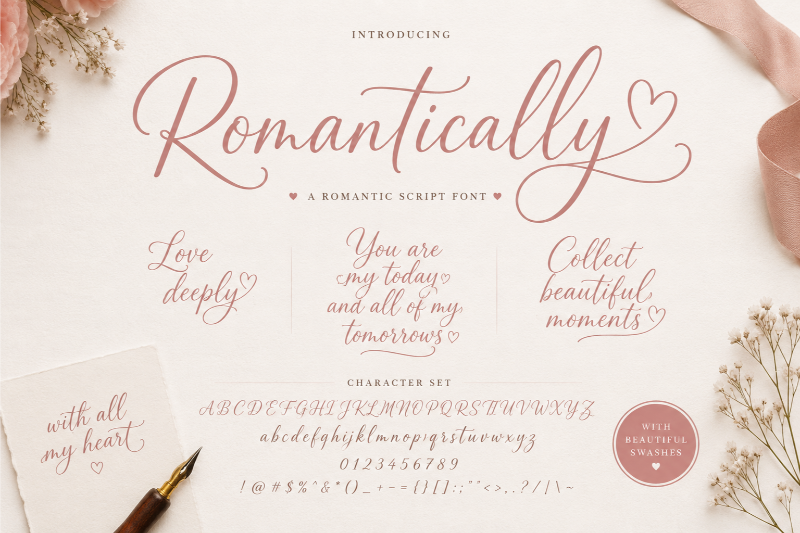
Rossela
Rossela tạo cảm giác hiện đại, thanh thoát và có độ quyến rũ vừa phải. Font không quá cầu kỳ nhưng vẫn đủ nổi bật, phù hợp với thương hiệu mỹ phẩm, thời trang nữ, spa hoặc các thiết kế cần sự sang trọng nhẹ nhàng.
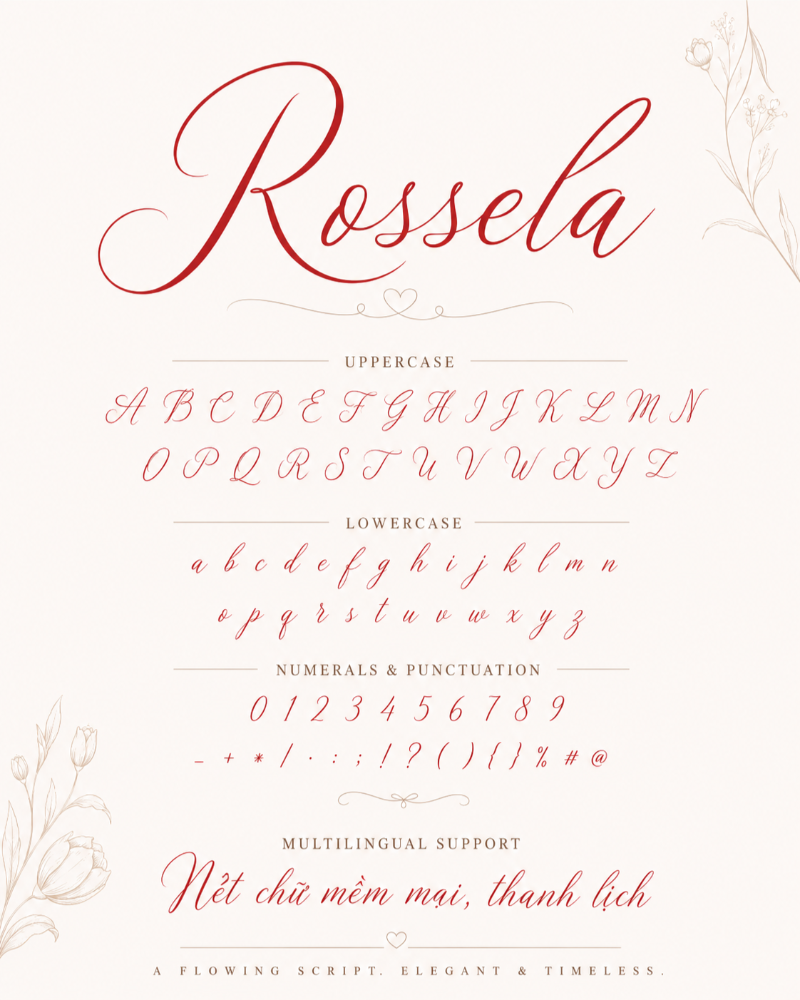
Imogen Agnes
Imogen Agnes gây ấn tượng nhờ nét chữ tự nhiên, giống chữ viết tay bằng bút mực. Các đường nét có cảm giác phóng khoáng, hơi vội nhưng vẫn sắc sảo. Font này phù hợp để làm chữ ký cuối bài blog, quote cảm xúc, watermark ảnh hoặc các thiết kế mang hơi hướng cá nhân.
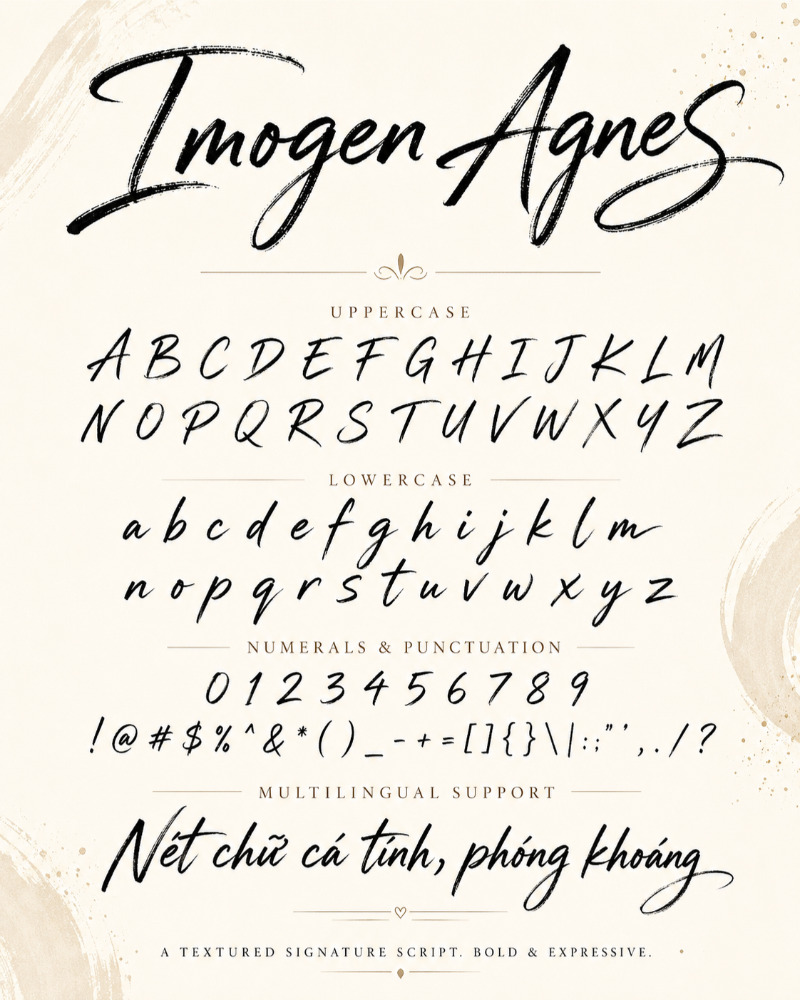
Hipsteria
Hipsteria mang màu sắc vintage rõ rệt, pha chút bụi bặm của văn hóa hipster. Nét chữ có phần thô, không quá trau chuốt nhưng lại tạo cảm giác rất nghệ thuật. Đây là lựa chọn phù hợp cho watermark nhiếp ảnh, logo quán cà phê, barber shop hoặc các thương hiệu theo phong cách đường phố.
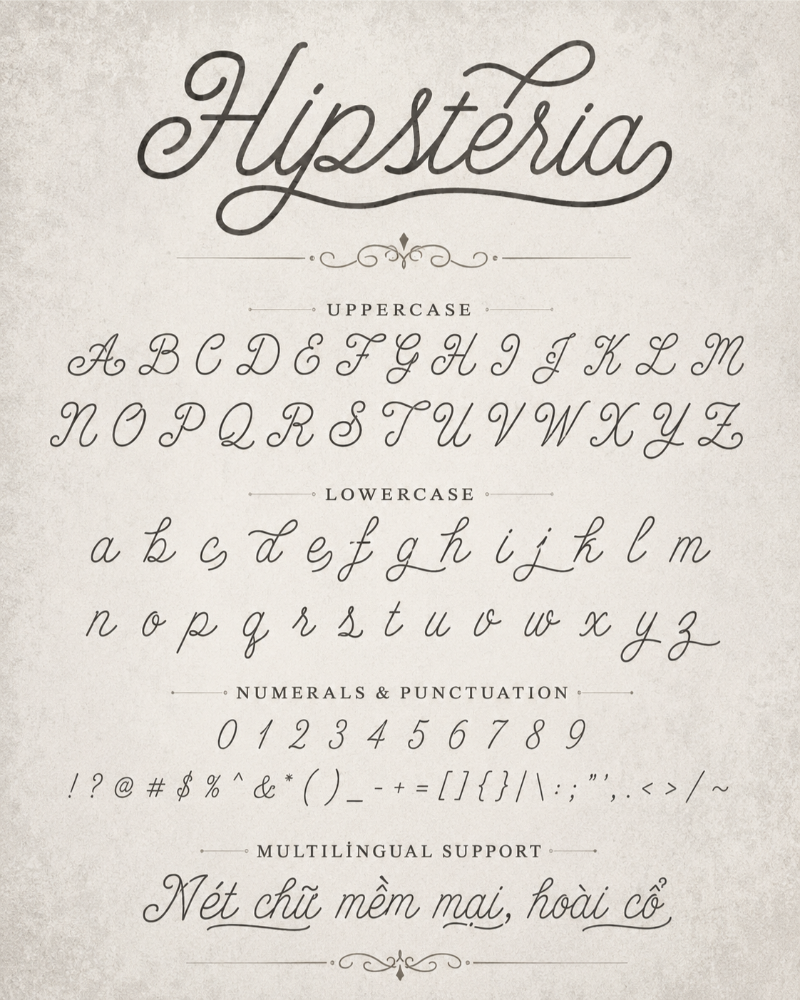
Just Awesome
Just Awesome nổi bật với nét chữ dày, mạnh và dứt khoát. Font này tạo cảm giác năng lượng, tự tin và rất dễ thu hút ánh nhìn. Bạn có thể dùng Just Awesome cho poster sự kiện, bìa album, banner quảng cáo hoặc các thiết kế cần sự cá tính rõ ràng.
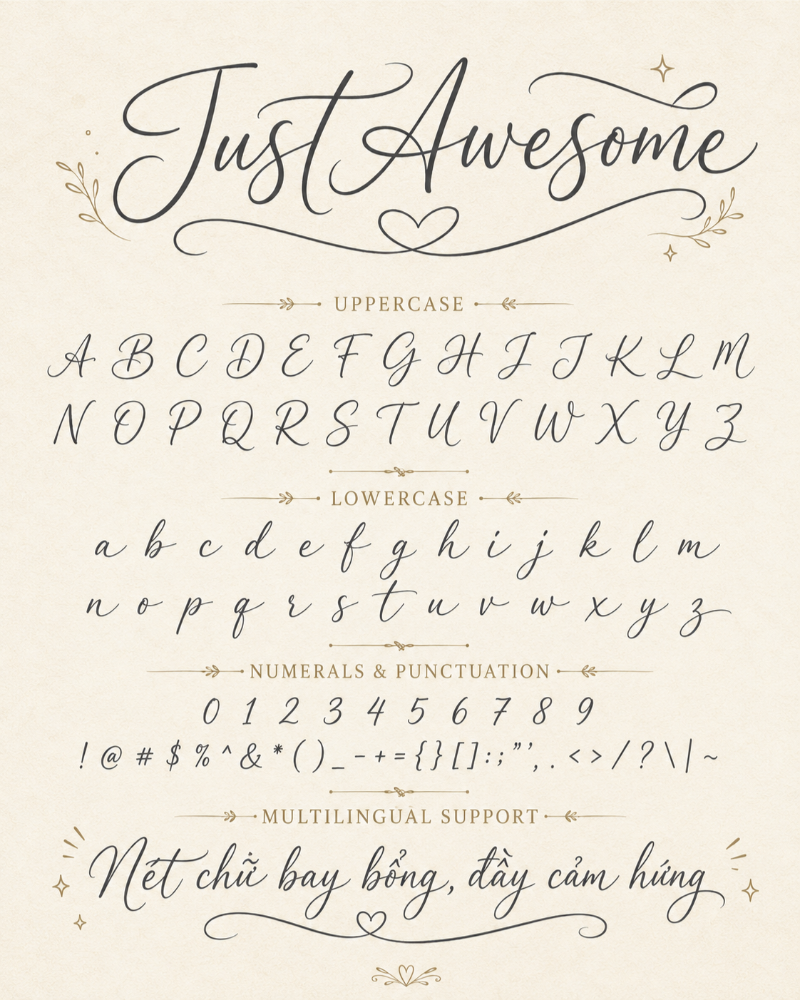
Bellwethers
Bellwethers có độ tương phản rõ giữa nét thanh và nét đậm, tạo cảm giác sang trọng và nghiêm túc. Font này giống một chữ ký được luyện tập cẩn thận, phù hợp với hình ảnh của chuyên gia, nhà văn, doanh nhân hoặc thương hiệu cá nhân cần sự uy tín.
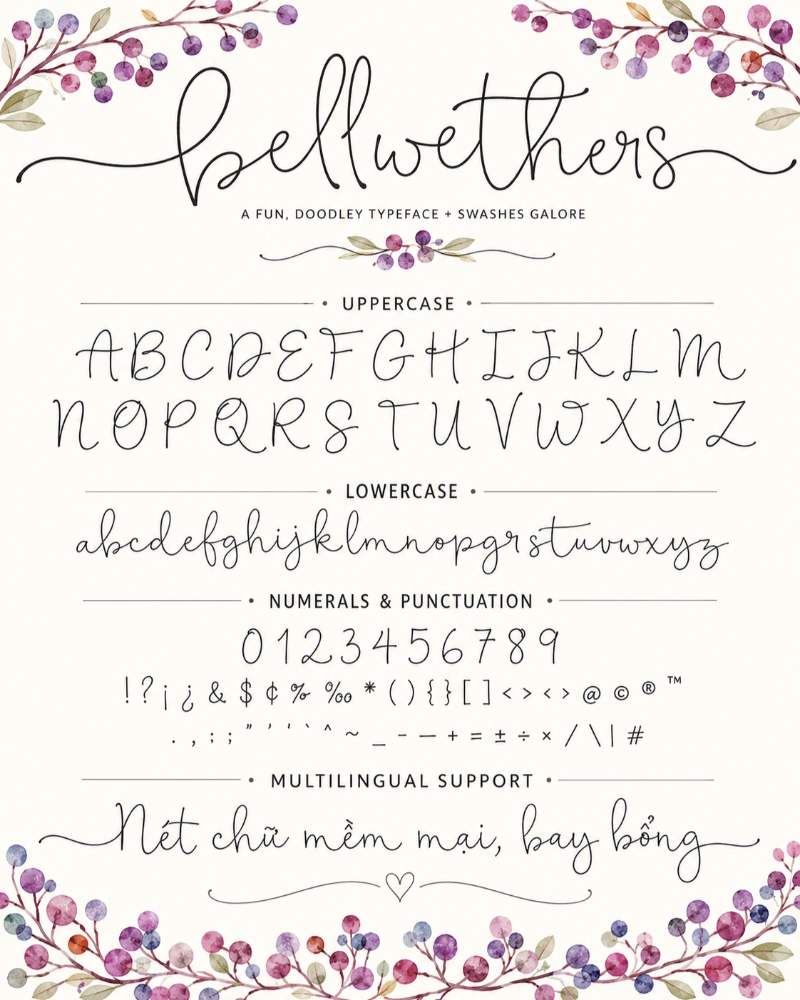
Scripture
Scripture có cấu trúc chữ đều, dễ đọc và không quá rườm rà. Font vẫn giữ được tinh thần của chữ ký nhưng không làm người xem bị rối mắt. Đây là lựa chọn an toàn cho logo, tiêu đề phụ, bao bì sản phẩm, name card hoặc các ấn phẩm cần sự chuyên nghiệp.
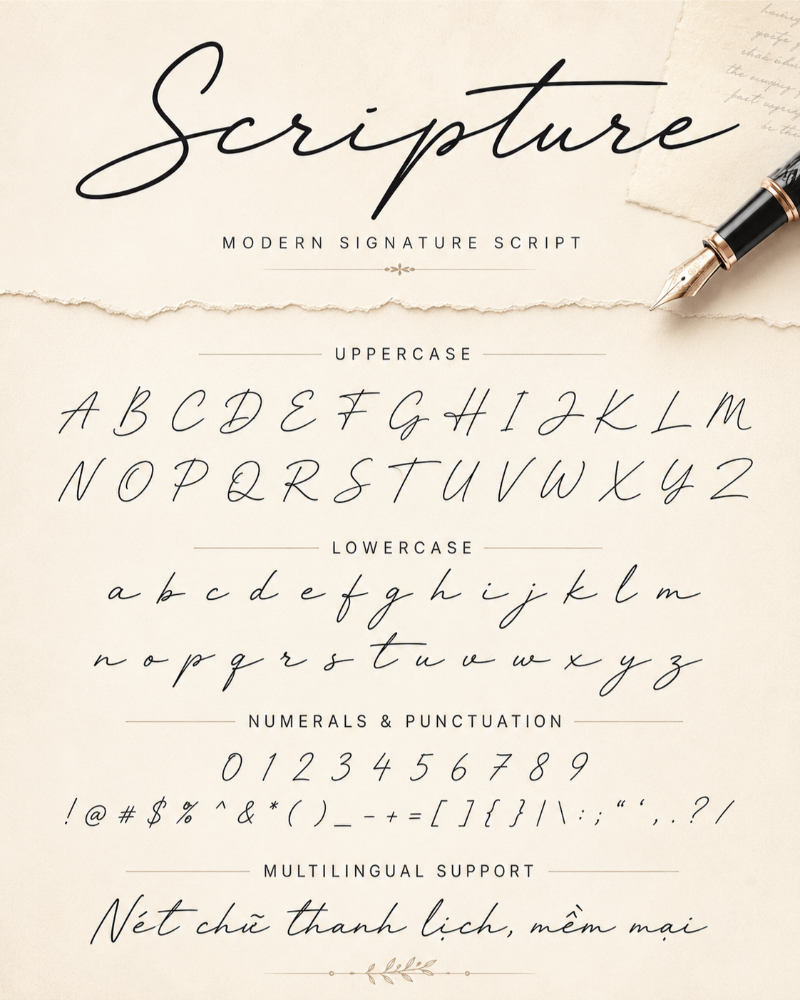
SVN-Astronout
SVN-Astronout là font chữ bay bổng, có nhiều nét nối dài ấn tượng. Font này không phù hợp để viết đoạn văn dài, nhưng rất nổi bật khi dùng cho tiêu đề, logo nghệ thuật, poster hoặc các thiết kế typography cần điểm nhấn mạnh.
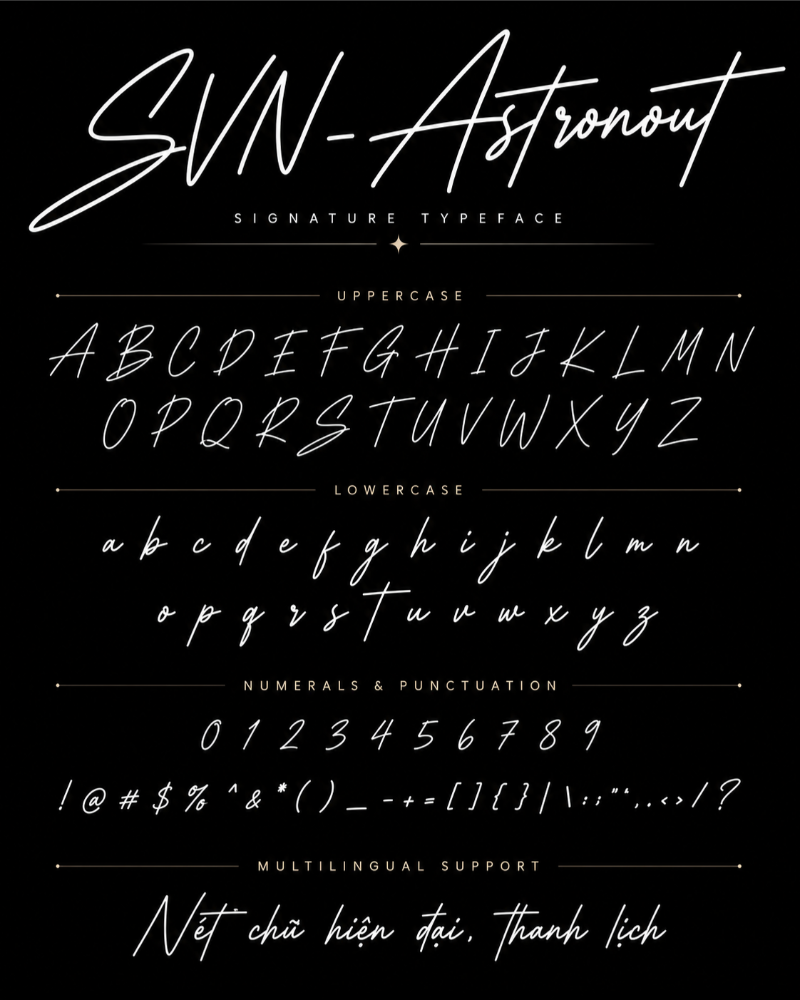
Lovepen Typeface
Lovepen Typeface mang cảm giác gần gũi như chữ viết tay bằng bút bi hoặc bút mực trên giấy. Nét chữ mộc mạc, tự nhiên và có chút hoài niệm. Font này phù hợp với thiết kế truyền tải thông điệp chân thành, nhật ký, quote nhẹ nhàng hoặc các sản phẩm mang cảm xúc cá nhân.
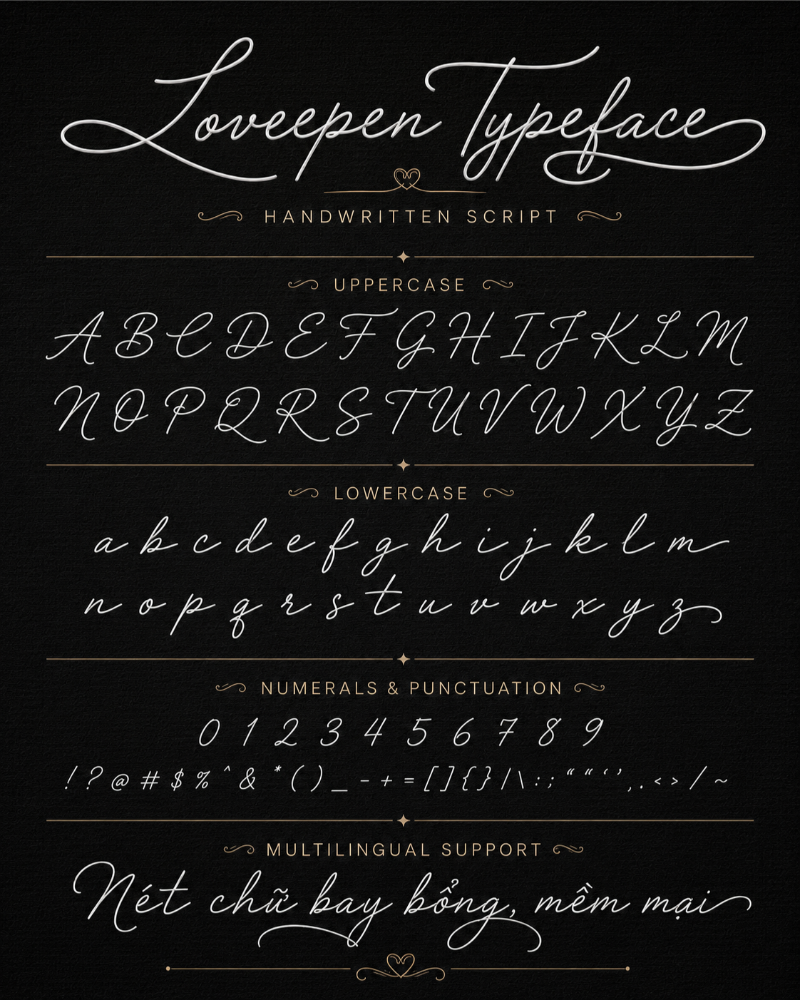
Like Father Like Son Typeface
Like Father Like Son Typeface có đường nét cứng cáp, rõ ràng nhưng vẫn giữ được chất thủ công. Font này gợi cảm giác nam tính, mạnh mẽ và giàu câu chuyện. Đây là lựa chọn phù hợp cho thiết kế về gia đình, thương hiệu cá nhân, sản phẩm thủ công hoặc các thông điệp truyền cảm hứng.
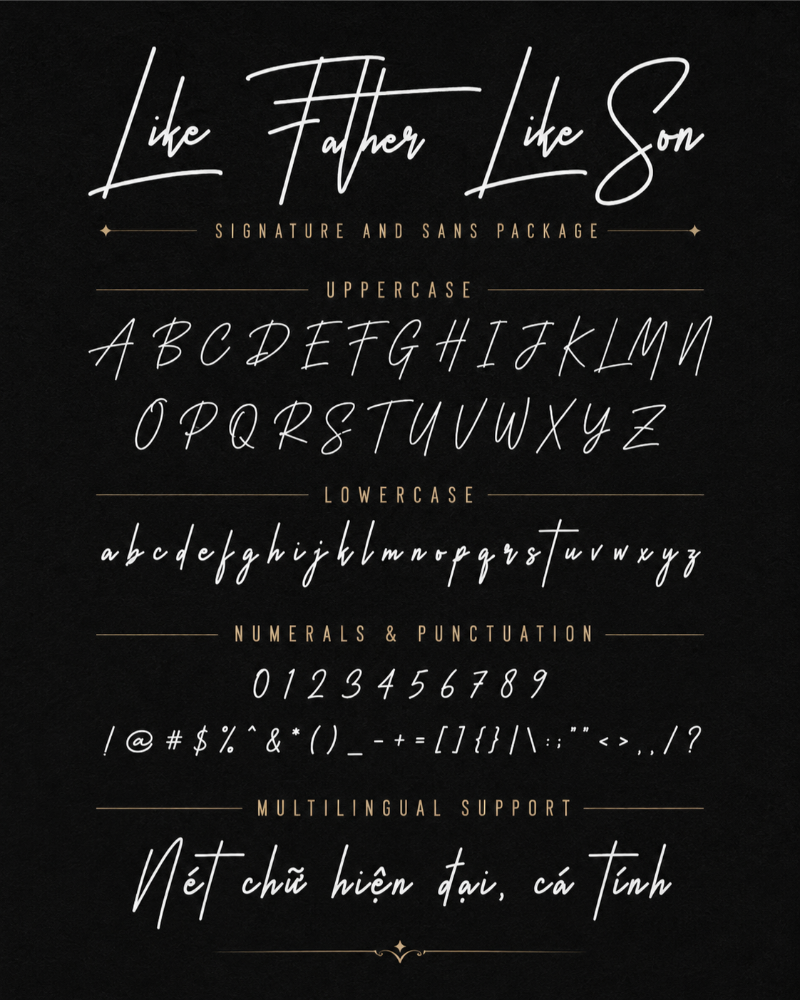
Mẹo phối font chữ ký để thiết kế trông tinh tế hơn
Có font chữ đẹp chưa đủ. Quan trọng hơn là bạn phải biết cách sử dụng và kết hợp font sao cho hài hòa. Nếu dùng sai, thiết kế rất dễ trở nên rối mắt, thiếu chuyên nghiệp. Dưới đây là 3 nguyên tắc bạn nên ghi nhớ.
Một font chữ ký phù hợp không chỉ giúp thiết kế trở nên nổi bật hơn mà còn thể hiện rõ cá tính, cảm xúc và tinh thần riêng của người sáng tạo. Hy vọng danh sách 10+ font chữ ký Việt hóa cùng các mẹo sử dụng trên sẽ giúp bạn có thêm nhiều lựa chọn hữu ích cho những dự án thiết kế sắp tới.